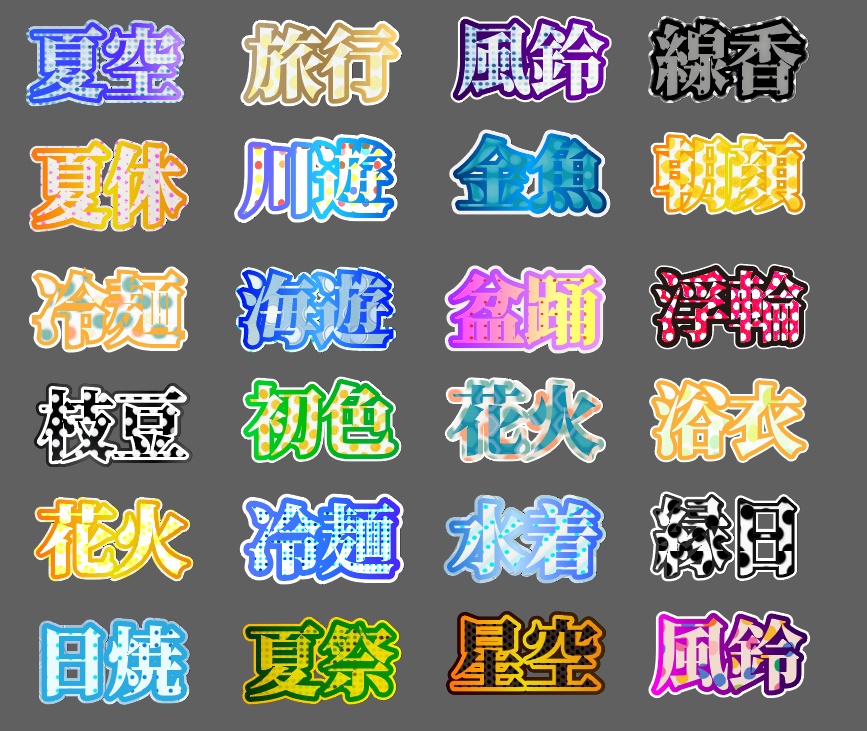
illustratorで使えるグラフィックスタイル全24種類【さわやか夏文字系フォント】
※商品内容 illustrator(イラストレーター)で使える、爽やかでかわいいポップな夏文字系フォントです。 ※当商品を利用するメリット ・外注費用をかけず自分で高クオリティーのYouTubeサムネイルの文字フォントを作成する事ができます。(お金の節約) ・シンプルなフォントからデザイン性の高いフォント装飾が多数あるので、自分のビジネスにあわせて利用する事で動画をみつけてもらいやすくなります(動画のクリック数に貢献します) ・1クリックで文字の装飾が適応できます。そのままフォントを利用できるので時間の節約につながります。 ・装飾も簡単でカラーや微調整も簡単に修正できます。 ・高品質なYoutubeサムネイル、WEBデザイン、LPページ、バナー広告等など、illustratorで作成する制作物にご利用いただけます。 利用規約 ・予告なく価格が変更する事があります(価格が上がる可能性があるため、購入を検討している方はお早めにご検討ください) ・Windowsで作成しています。Macをお使いの方は、【CubeICE】等で対応できるかもしれません。開けない場合は自己責任になりますがデーター上の問題によりキャンセルの対応はできません。 ・Adobeillustrator 28.0で作成しています。それよりも前のバージョンでは作動しない場合がございます。 ・購入者以外の使用を禁止しております。また、再配布、譲渡、転用、再販は禁止しております。 ・こちらの商品は利用者一人につき1つ購入が必要です。1つ購入して会社内やチームで共有する事は二次配布や譲渡、コピーになるので禁止しています。 ・それ以外の利用については商用・非商用に限らず自由にお使いください。 ■以下の文字フォントを利用しています。 ・げんのみんちょう ダウンロードしていただいた時にそのPCにフォントデザインがないと文字が崩れる可能性があるので、似たようなデザインにしたい場合はAdobeフォントでダウンロードをお願いします。